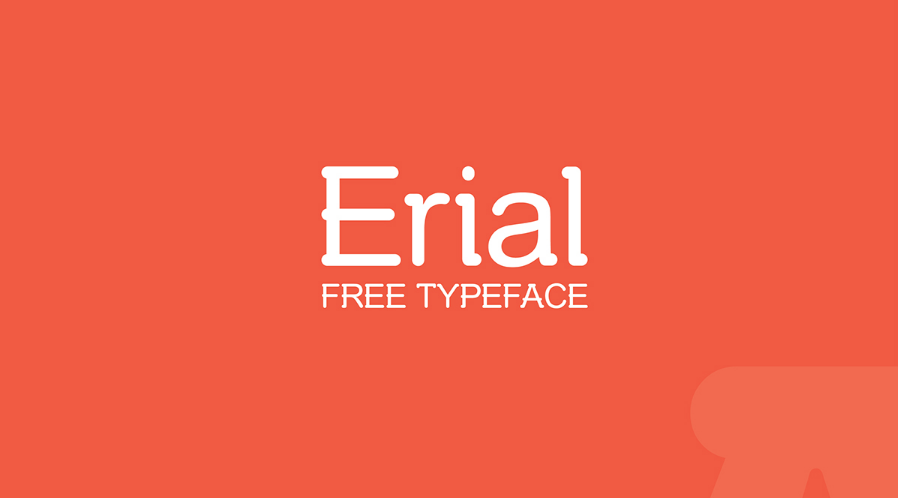
Erial Typeface – Fonte Grátis
Erial Typeface
A Erial Typeface é uma elegante família de serif que combina sofisticação com conforto para projetos que valorizam estilo detalhado. Seu designer, Hamilton, criou esta fonte cuidadosamente para oferecer uma experiência visual suave e profissional. Com linhas bem definidas e tramas suaves nas bordas dos caracteres, a Erial é perfeita para criações de texto que exigem uma aparência clássica e atemporal. Estilizada para textos legíveis em grandes tamanhos, a Erial oferece um equilíbrio entre simplicidade e refinamento. Perfeitamente adequada para portfólios profissionais, cartazes de marketing ou qualquer projeto que desejasse destacar o texto com uma aparência sólida e bem pensada. Suas linhas precisas garantem que a Erial se destaque entre seus concorrentes em qualquer ambiente visual.